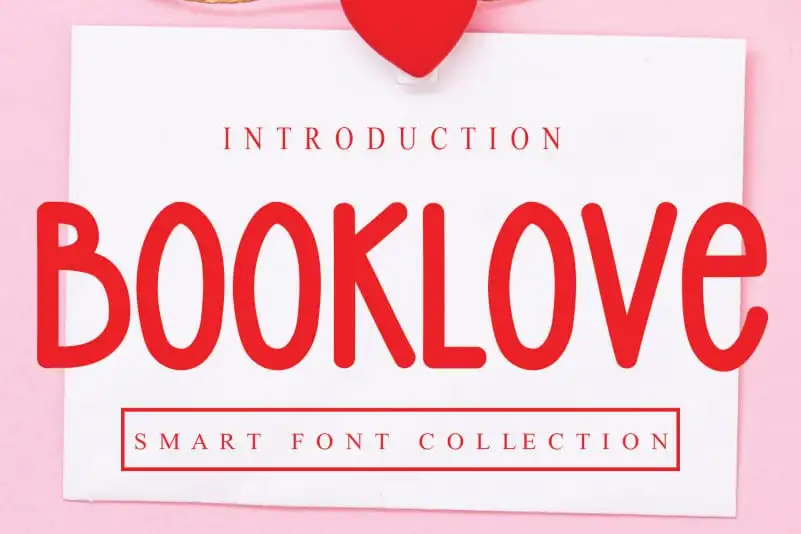
Booklove Display Font – Download Grátis
A fonte Booklove Display Font é ideal para aqueles que procuram uma experiência única e criativa no design do layout de seus projetos. Com sua tipografia expressiva e moderna, esta fonte oferece um toque especial ao texto, tornando-a perfeita para anúncios e designs gráficos onde deseja chamar a atenção dos leitores. Inspirada em uma gama de estilos diferentes, desde elegância até o desenho vanguardista, a Booklove Display Font proporciona um encantamento visual que vai ao encontro do seu projeto específico. Como resultado da experiência criativa dos designers da creativeletter, cada caractere desta fonte é cuidadosamente concebido para dar vida aos seus projetos de design. Adicionalmente, esta fonte permite que você faça seu texto destacar-se com um tom vibrante e único, garantindo que todos os olhos estejam focados no conteúdo que deseja transmitir. Com a Booklove Display Font, transforme o simples em extraordinário, adicionando personalidade aos seus designs para criar uma experiência de leitura única e memorável.